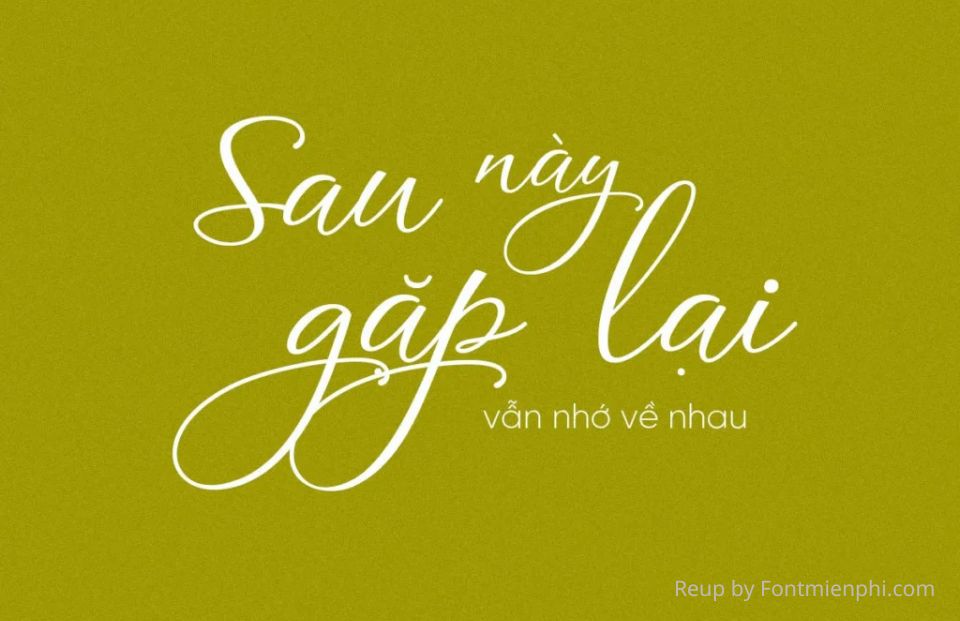
Font VL Agile Script Calligraphy Việt Hóa Miễn Phí 2026
Fontmienphi.com Giới Thiệu: Font VL Agile Script Calligraphy Việt Hóa Miễn Phí – Nét Bút Cổ Điển & Trang Trọng
Nếu dự án thiết kế của bạn đang cần một điểm nhấn mang đậm chất hoài cổ nhưng không kém phần sang trọng, thì đây chính là lựa chọn hoàn hảo. Là một kiểu chữ mang phong cách Calligraphy (thư pháp phương Tây) cổ điển, VL Agile Script nổi bật với những đường nét cầu kỳ, uốn lượn, chắc chắn sẽ làm say đắm mọi ánh nhìn.
🌟 Đặc Điểm Nổi Bật Của Font VL Agile Script Calligraphy Việt Hóa Miễn Phí
Khác với những phông chữ thông thường, VL Agile Script Calligraphy mang trong mình một linh hồn nghệ thuật rất riêng:
• Phong cách viết tay cổ điển: Tái hiện lại những nét bút mực hoa mỹ của giới quý tộc xưa, mang đến cảm giác hoài niệm và tinh tế.
• Ký tự kéo dài đầy nghệ thuật: Các nét lượn (swash) và phần đuôi chữ được kéo dài một cách điệu đà, tạo nên sự cầu kỳ và một vẻ đẹp vô cùng trang trọng.
• Tôn vinh sự sang trọng: Tổng thể phông chữ toát lên một đẳng cấp khác biệt, rất phù hợp cho những dự án đòi hỏi tính thẩm mỹ cao.
• Việt hóa chuẩn mực: Đã được xử lý dấu tiếng Việt mượt mà, giúp bạn tự do sáng tạo nội dung mà không lo gãy nét.
🎨 Ứng Dụng Hoàn Hảo Trong Thiết Kế Font VL Agile Script Calligraphy Việt Hóa Miễn Phí
Với vẻ đẹp cầu kỳ và lộng lẫy, VL Agile Script Calligraphy sẽ tỏa sáng rực rỡ nhất khi được áp dụng vào:
• Thiết kế thiệp cưới, thiệp mời sự kiện cao cấp.
• Trình bày các ghi chú, thư tay hoặc thông điệp mang tính cá nhân hóa sâu sắc.
• Giấy chứng nhận, bằng khen và các tài liệu cần sự trang trọng tuyệt đối.
• Thiết kế logo, nhãn mác (packaging) cho các thương hiệu mỹ phẩm, trang sức, thời trang vintage.
💡 Bí Quyết Sử Dụng Font Hiệu Quả (Và Những Sai Lầm Cần Tránh)
Để khai thác tối đa vẻ đẹp của Font VL Agile Script Calligraphy Việt Hóa Miễn Phí 2026 , bạn cần lưu ý:
• Sử dụng đúng mục đích: Vì các đường nét khá cầu kỳ, hãy chỉ dùng font này cho phần Tiêu đề (Heading), tên riêng hoặc các cụm từ ngắn cần nhấn mạnh.
• Tránh dùng cho văn bản dài: Một sai lầm phổ biến là dùng font thư pháp cho toàn bộ đoạn văn (body text). Điều này sẽ làm giảm tính dễ đọc và gây rối mắt người xem.
• Kết hợp hài hòa: Hãy thử kết hợp (pair font) VL Agile Script với một phông chữ Serif hoặc Sans-serif đơn giản để tạo ra sự cân bằng hoàn hảo cho tổng thể thiết kế.